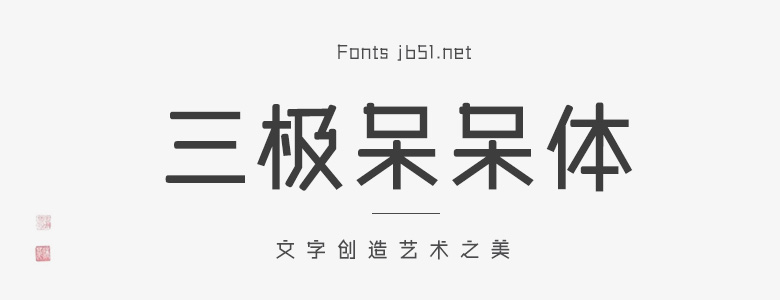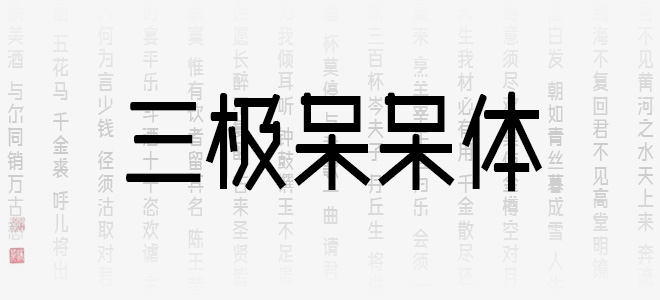
三極呆呆體是一款幾何型構(gòu)成的作品。整體風(fēng)格率真,直接。字體穩(wěn)重簡潔,筆畫平直、粗細勻稱,起筆為圓頭溫柔可愛,收筆平直天真率氣,又有強烈的個性。風(fēng)格年輕、富有親和力。它的靈感來源于管狀物體,直接簡單,堅韌不屈,給人一種直接干練的感覺。視覺效果簡單易識別,實用性強。本作品適用于傳統(tǒng)印刷媒介的標題、各類屏幕顯示及影視字幕等。歡迎喜歡三極呆呆體的朋友前來下載使用。
三極呆呆體